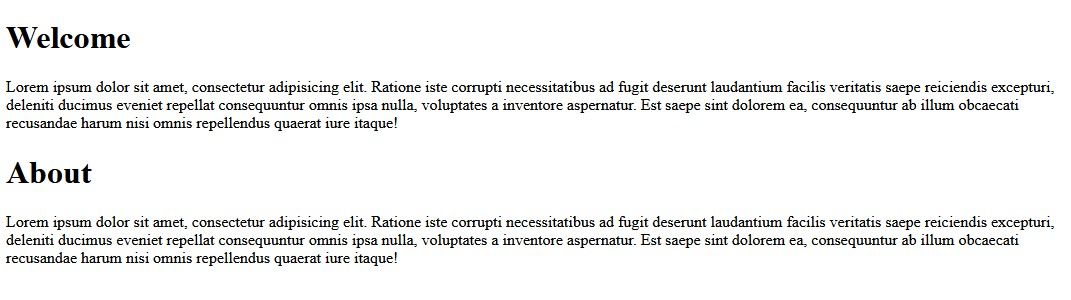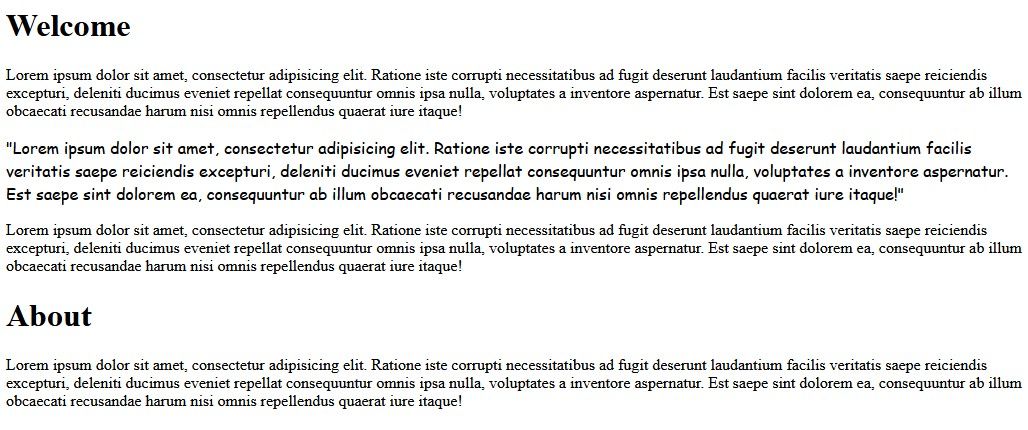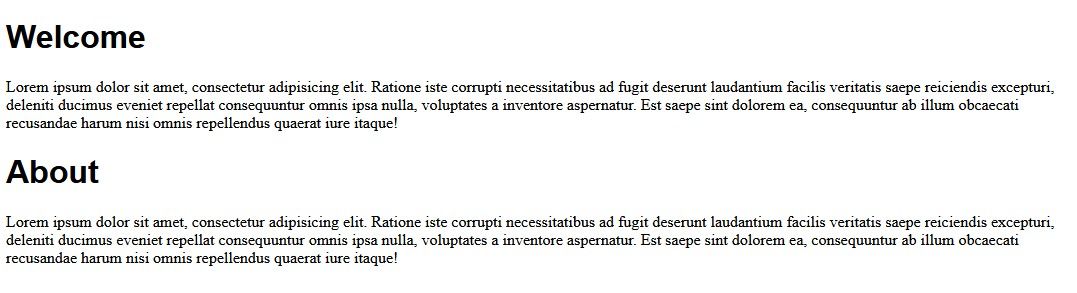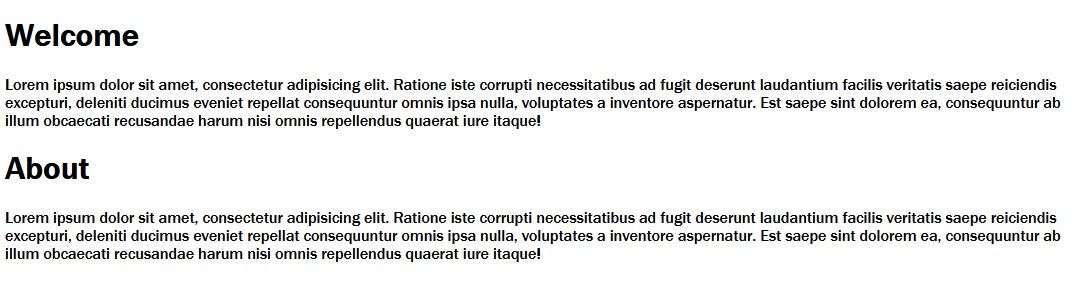
Как менять шрифты на сайте с помощью CSS‑свойства font-family
CSS font-family: как менять шрифты на сайте
Вы можете управлять стилем текста на веб‑странице с помощью CSS: менять цвет, выравнивание, размер и, конечно, сам шрифт. Свойство font-family отвечает за выбор типа шрифта. В этой статье подробно разберём синтаксис, поведенческие особенности запаса шрифтов, реальные примеры, альтернативы и проверки качества при внедрении шрифтов в проект.
Что такое роль текста на сайте
Текст — основной способ донести информацию до пользователя: заголовки, инструкции, формы, кнопки, контент статьи. Если шрифт плохочитаем или отсутствует, пользователь не поймёт интерфейс, что уменьшает эффективность сайта. При выборе шрифтов важно помнить о контрасте, размере и совместимости с платформами.
Определение: запасной шрифт — это следующий в списке шрифт, который использует браузер, если предыдущий недоступен.
Что такое свойство font-family
font-family — CSS‑свойство, которое задаёт список шрифтов (стек). Браузер проверяет в порядке приоритета: первый, затем второй и так далее. В конце стека обычно указывают общее семейство (generic family): serif, sans-serif, monospace, cursive, fantasy.
Правила:
• Шрифты разделяются запятыми.
• Если имя шрифта содержит пробел, берите его в одинарные или двойные кавычки.
• Последнее значение часто — общее семейство как гарантия отображения.
Синтаксис font-family
selector {
font-family: firstFontType, 'second font type', genericFontType;
}
selector может быть тегом (body, h1, p), классом или id. Часто прописывают font-family на body, чтобы базовый шрифт применялся ко всей странице.
Общие семейства шрифтов
• serif — с засечками (Times, Georgia)
• sans-serif — без засечек (Arial, Helvetica)
• monospace — фиксированная ширина символов (Courier, Consolas)
• cursive — рукописные или курсивные стили
• fantasy — декоративные дисплейные шрифты
Примеры использования font-family
Браузеры по умолчанию отображают текст шрифтом системы, если вы не указали свой стек. Ниже несколько рабочих примеров.
Шрифт по умолчанию в браузере на веб-странице
Задать шрифт для всего сайта (body)
body {
font-family: 'Franklin Gothic Medium', 'Arial Narrow', Arial, sans-serif;
}
В этом стеке приоритет такой: Franklin Gothic Medium → Arial Narrow → Arial → любой доступный sans-serif.
Пример шрифта Franklin Gothic на веб-странице
Разница заметна: Franklin Gothic относится к sans-serif, тогда как Times — к serif.
Локальная замена шрифта для блока или параграфа
#content-1 {
font-family: 'Courier New', Courier, monospace;
}
Это полезно для блоков с кодом, цитат или таблиц, где нужна фиксированная ширина символов.
Разные шрифты в блоках цитат на странице
Шрифт для заголовков
h1 {
font-family: Arial, Helvetica, sans-serif;
}
Заголовки будут в Arial, а тело документа останется в системном шрифте.
Применение селектора h1 для изменения шрифта заголовков
Когда простой стек шрифтов не подходит
• Шрифт отсутствует на устройстве пользователя: если вы рассчитываете на кастомный шрифт, которого нет в системе, браузер выберет запасной.
• Нужен фирменный дизайн: если бренд требует уникальный шрифт, придётся подключать веб‑шрифт.
• Контроль загрузки и CLS: подключённые веб‑шрифты могут влиять на перерисовку страницы и скачивание ресурсов.
Альтернативные подходы и подключение веб‑шрифтов
1. @font-face — встроенный механизм для загрузки и использования собственных файлов шрифтов.
@font-face {
font-family: 'MyBrand';
src: url('/fonts/MyBrand-Regular.woff2') format('woff2'),
url('/fonts/MyBrand-Regular.woff') format('woff');
font-weight: 400;
font-style: normal;
font-display: swap;
}
body {
font-family: 'MyBrand', system-ui, -apple-system, 'Segoe UI', Roboto, 'Helvetica Neue', Arial, sans-serif;
}
Пояснение: font-display управляет стратегией отображения шрифта (auto, block, swap, fallback, optional). swap — быстрый, сначала показывается запасной шрифт, затем происходит замена на загруженный.
1. Сервисы веб‑шрифтов (Google Fonts, Adobe Fonts) — удобны, но добавляют внешние запросы и зависят от политики конфиденциальности.
2. Переменные шрифты (variable fonts) — один файл вместо набора весов, уменьшает общий объём, но требует поддержки браузеров и тестирования.
Производительность и оптимизация загрузки шрифтов
• Используйте формат WOFF2, где это возможно — он эффективнее по размеру.
• Предзагрузка критических шрифтов:
• Используйте font-display: swap или optional, чтобы избежать «невидимого текста» (FOIT).
• Уменьшайте число подключаемых весов и стилизаций (italic), бережно относитесь к латинским и кириллическим наборам.
• Кеширование через заголовки кеширования и CDN ускорит доставку.